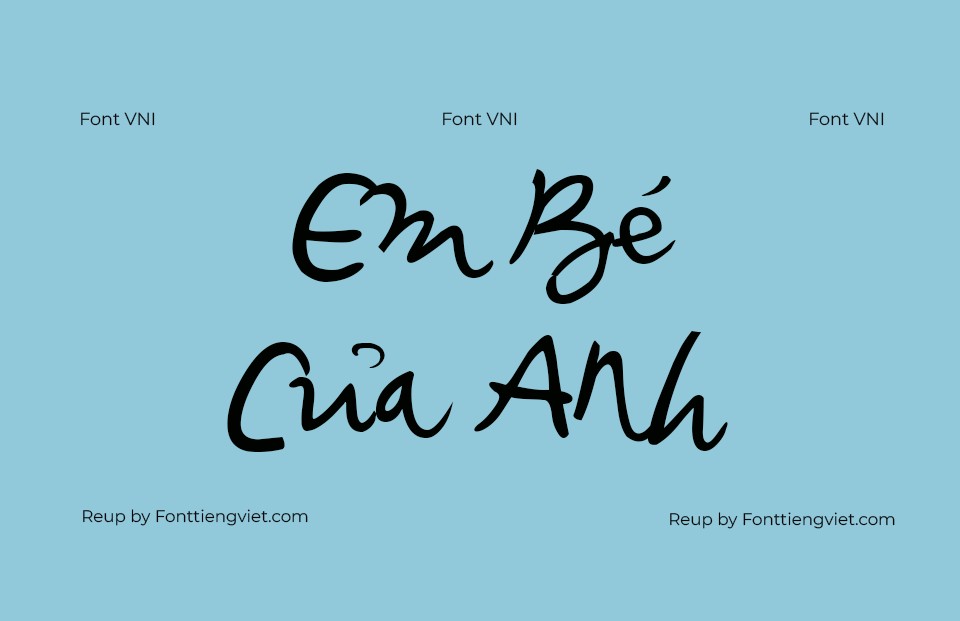
Giới thiệu về Font Việt hoá VNI Baybuom
Trong thế giới thiết kế đồ họa, việc lựa chọn một Font Miễn Phí phù hợp là yếu tố then chốt giúp tác phẩm trở nên thu hút. Font Việt hoá VNI Baybuom là một trong những bộ phông chữ nghệ thuật được ưa chuộng nhất hiện nay nhờ đường nét bay bổng và mềm mại. Bộ phông này không chỉ mang đậm giá trị thẩm mỹ mà còn được tối ưu hóa hoàn toàn cho tiếng Việt, giúp người dùng dễ dàng ứng dụng vào các phần mềm thiết kế phổ biến. Với phong cách uyển chuyển như những cánh bướm, đây là lựa chọn lý tưởng cho các biểu ngữ, thiệp chúc mừng hay các dự án giáo dục tại nhà trường.
Ưu điểm của Font Việt hoá VNI Baybuom trong thiết kế
Nét chữ nghệ thuật độc đáo
Đặc điểm nổi bật của Font Việt hoá VNI Baybuom chính là sự kết hợp tinh tế giữa nét thanh và nét đậm. Từng ký tự được tạo hình tỉ mỉ, gợi lên cảm giác nhẹ nhàng nhưng vẫn giữ được sự rõ ràng khi đọc. Điều này đặc biệt hữu ích cho các bạn học sinh khi muốn trang trí báo tường hoặc làm thiệp tặng thầy cô, giúp nội dung trở nên sinh động và giàu cảm xúc hơn.
Khả năng tương thích linh hoạt
Kết luận và cách sử dụng hiệu quả